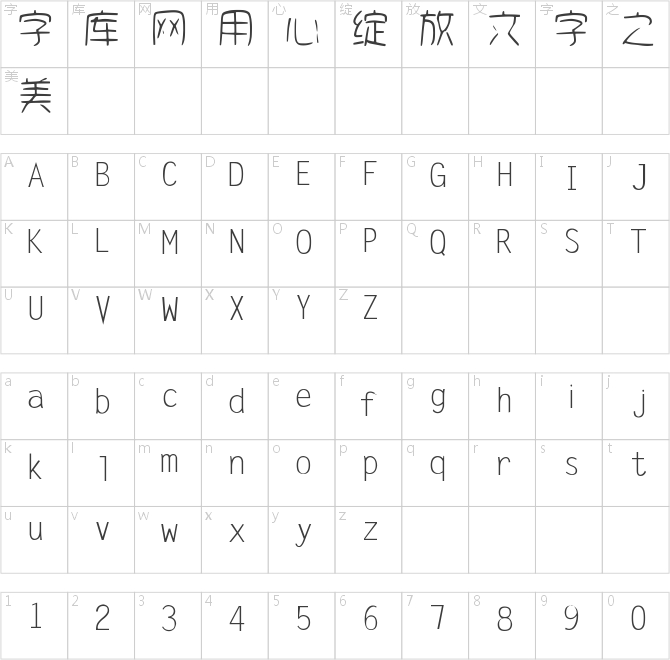
字体家AI造字柒恒
这是一款由字体家AI神笔造字生成的一款字体,字体线条圆润流畅,没有棱角,整体呈现出柔和、优美的视觉效果。给人以温润、舒适的感受,展现出一种柔美的美感。
比较适合用于海报、品牌包装以及广告等载体应用等。
字体家AI造字柒恒字体字库是一款让人赏心悦目、百看不厌的中文字体,适合各类广告和产品包装设计应用,字体大小4.87MB,格式为ttf字体,上传用户是舒甜咖啡,作者/版权方为字体家